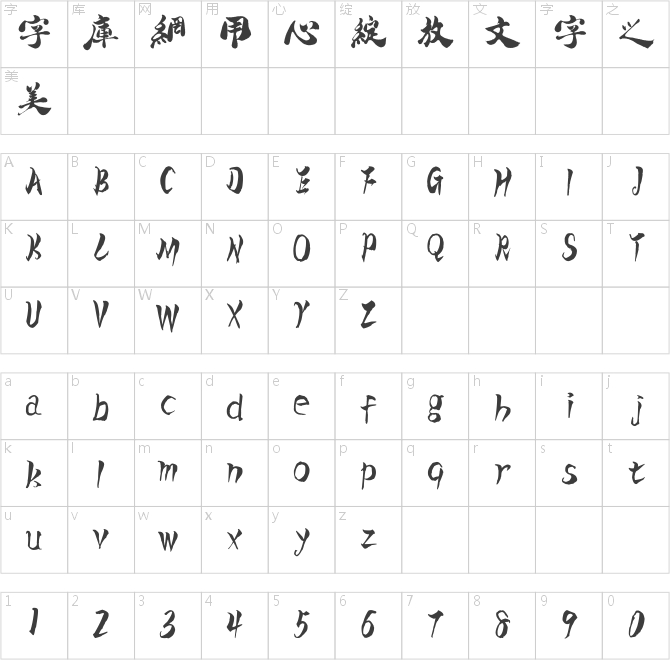
漢標(biāo)難得糊涂體
漢標(biāo)難得糊涂體字體字庫(kù)是一款讓人賞心悅目、百看不厭的中文字體,適合各類廣告和產(chǎn)品包裝設(shè)計(jì)應(yīng)用,字體大小16.78MB,格式為ttf字體,上傳用戶是漢標(biāo)文創(chuàng),作者/版權(quán)方為漢標(biāo)